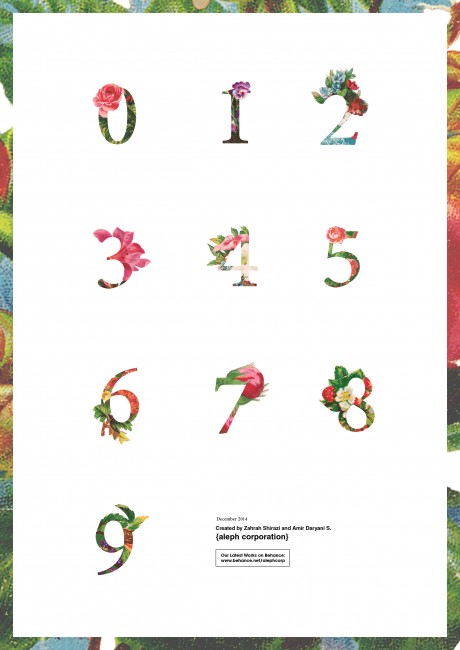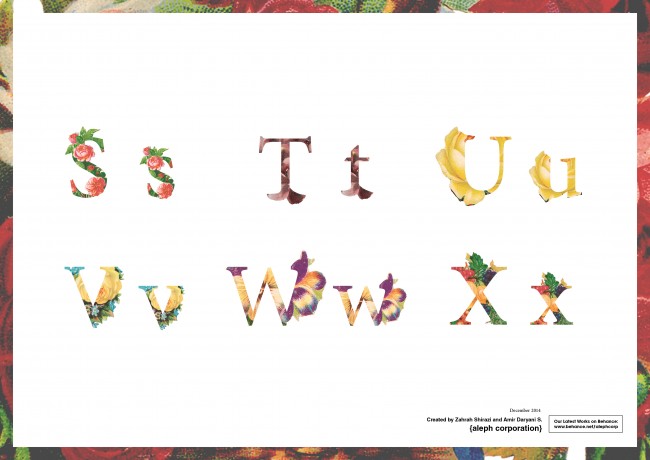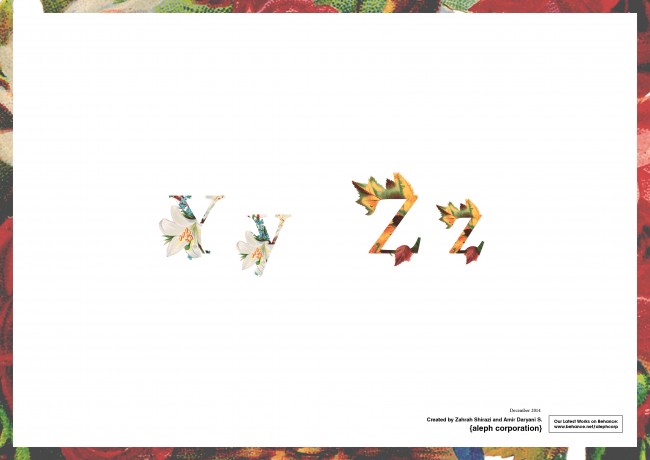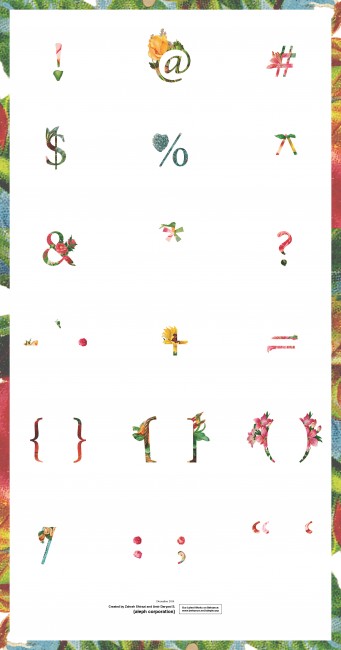
花がらの超おしゃれなフォントデザイン(商用可) Vintage & Eroded Font
Vintage & Eroded Fontは花がらが素敵でおしゃれなフォントデザインです。
全てのフォントがかなり凝った作りになっています。南国のカラフルな花というイメージですね。
↓ABCDEF
↓GHIJKL
↓MNOPQR
↓STUVWX
↓YZ
YZ {Vintage Font by aleph corp}
↓数字もあります。
↓なんと色々な記号まで揃っています!